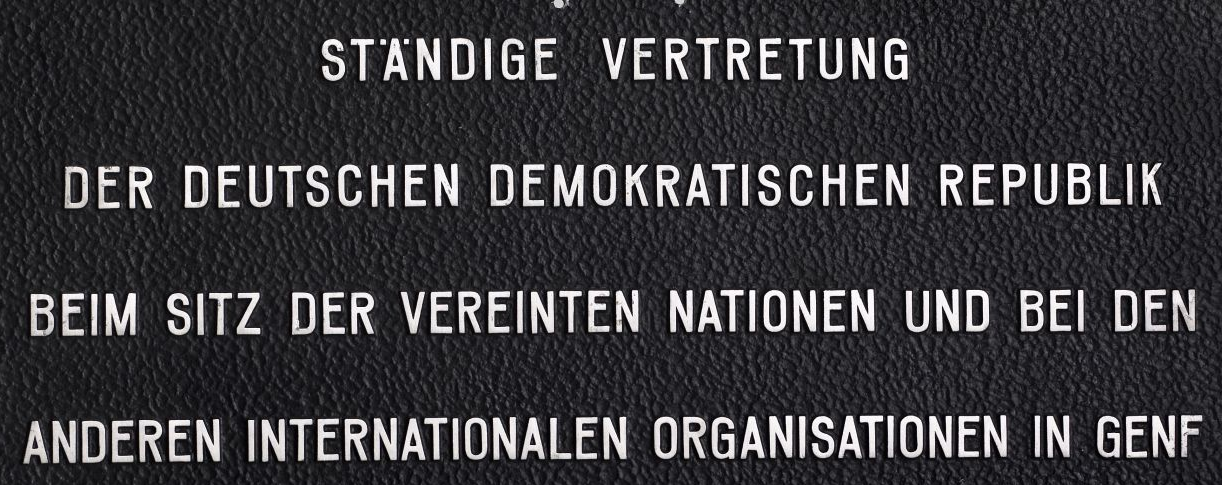
Suche Schriftart: "Ständige Vertretung"
ich suche die Schriftart die auf diesem Schild der Ständigen Vertretung der DDR verwendet wurde – vermutlich aus den 70er Jahren.
Whatthefont hat leider nichts Verwendbares ausgespuckt.